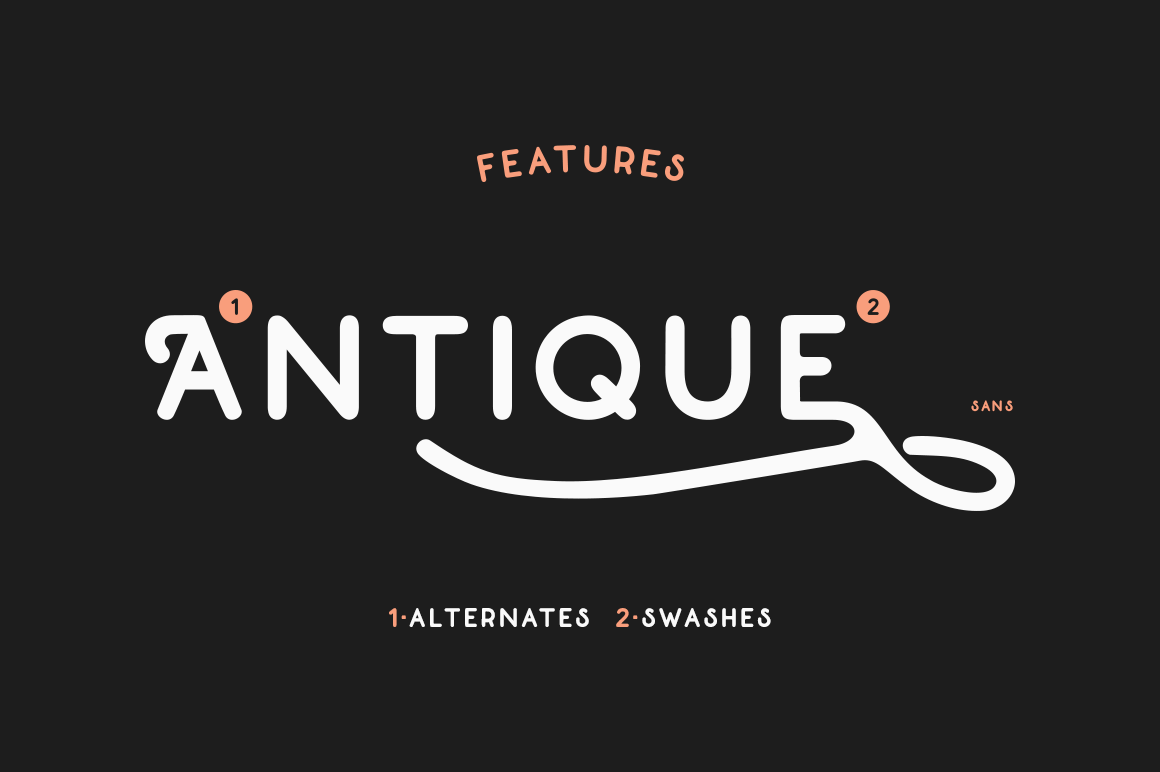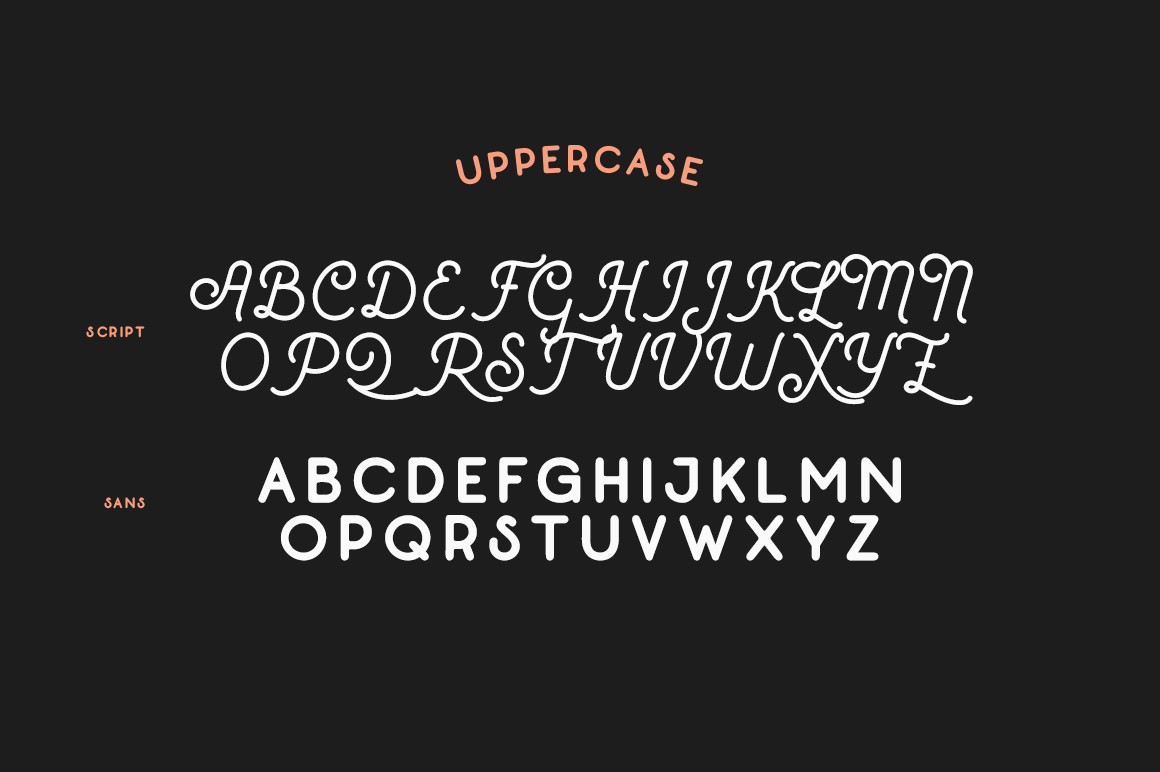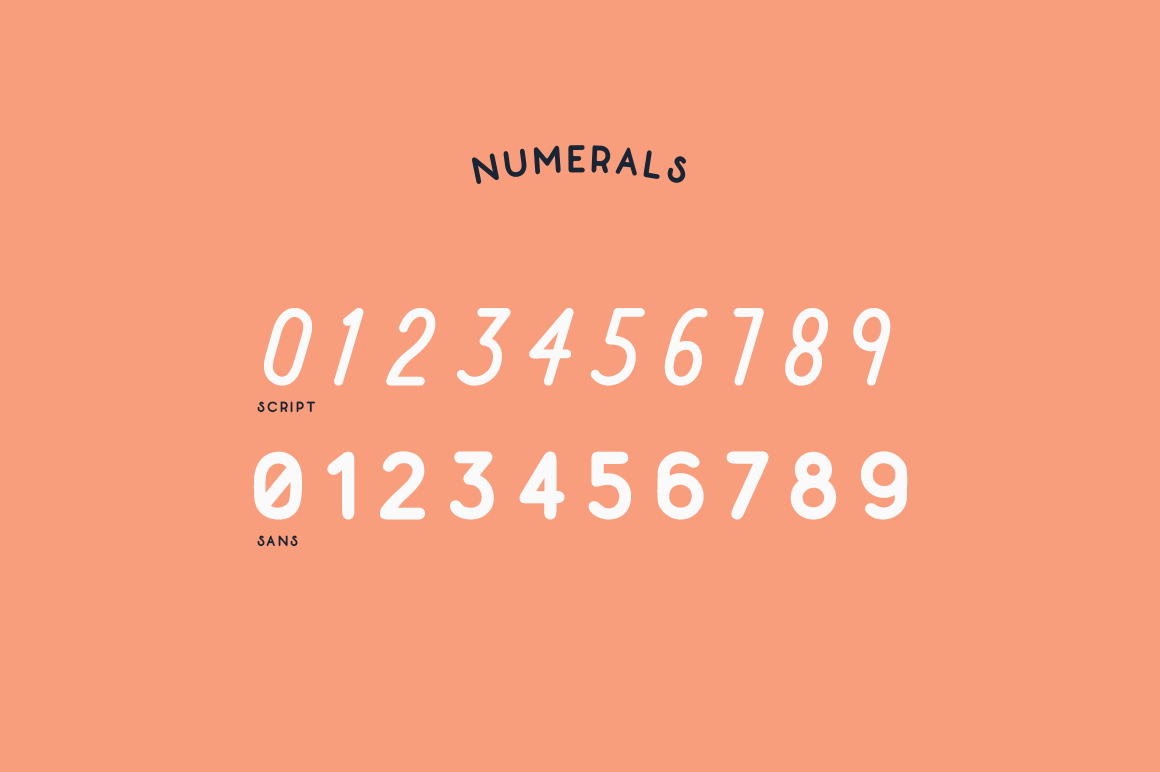
Belvederefont DuoDemoisamono Line Fontdu,这是两个重要年代的照相样式所采用的字体,其年代超过了40年代和50年代。该家族的年份由单重草书和无衬线的补充组成。所有字符均经过设计,以提高整体平滑度,这两种语言都有助于最大限度地提高可读性。Belved对于家庭来说是通用的,在商业版本中,它包括400多个字符,涵盖了基于拉丁字母表的多种语言;整个设计还包括广泛的替代物、结扎物和Swashessets。该FontDu适用于各种设计目的,如徽标、徽章、服装、海报等。